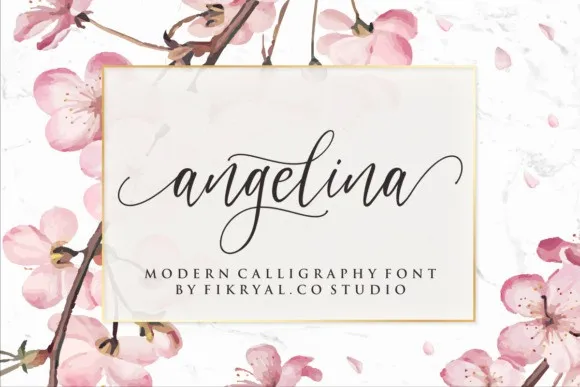
Angelina – Gorgeous Script Font – Download Grátis
A Angelina é uma maravilhosa fonte de script, criada por mfikryalif para designers apaixonados que buscam uma fonte elegante e com personalidade. Esta fonte está disponível como um kit completo de letras maiúsculas e minúsculas, assim como sinais gráficos variados, números e suporte multilíngue. Ela carrega o encanto da calligrafia em cada letra, tornando-a perfeitamente apropriada para criar designs excepcionais. Com seu design elegante e sua personalidade descontraída, Angelina é uma ótima escolha para qualquer projeto que você esteja desenvolvendo. É ideal para uso em rótulos de marca, cabeçalhos de redes sociais, embalagens de produtos, convites de casamento e muito mais. Engane-se ao pensar que ela é apenas uma fonte; Angelina também proporciona aos designers a oportunidade de transformar qualquer ideia de design numa verdadeira obra-prima. Através deste conjunto de recursos únicos e extremamente detalhado, a fonte Angelina se destaca não só como uma fonte de calligrafia, mas também como um recurso valioso para qualquer projeto de design gráfico.